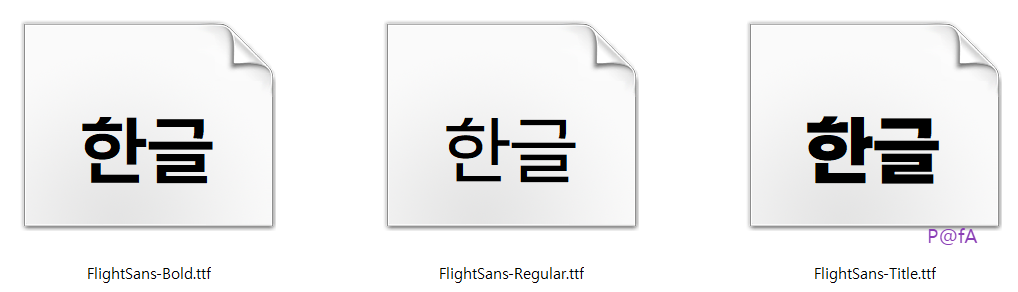
제주항공에서 2024년 한글날을 기념해서 무료로 배포하는 폰트인 제주항공 플라이트 산스를 다운로드하는 방법을 살펴본다. 더불어 누구나 무료로 사용이 가능한 제주항공 플라이트 산스를 윈도우에 설치하는 방법과 코딩 시에 사용하는 방법도 살펴본다.
누구나 개인적인 용도뿐만 아니라 상업적인 용도 즉, 영리 또는 비영리 목적으로도 무료로 사용할 수 있도록 제공하는 무료 글꼴인 제주항공 플라이트 산스를 소개한다. 2024년에 배포한 제주항공 플라이트 산스는 굵은 글꼴인 볼드 형태의 제목용 1종과 본문용 2종으로, 한글 4600자를 비롯하여 영문 300자, 기호 활자 970자 그리고 딩벳 20자로 제작됐다. 다음에서 제주항공 플라이트 산스를 무료로 다운로드해서 컴퓨터에 설치하는 방법을 비롯해서 사용하는 자세한 방법을 확인할 수 있다.
상기 이미지에서 보듯이 하늘에서 상단의 ㅎ의 상단 획에서 상승감과 ㅏ에 담긴 유연한 곡선감으로 제주항공을 상징하는 비행기의 움직임을 형상화하고 있다. 특히 ㅎ에서 보듯이 꼭지에 잉크트랩을 적용하여 비행기 날개와 닮은 개성을 적극 반영하여 동적인 느낌을 전달하고 있다.